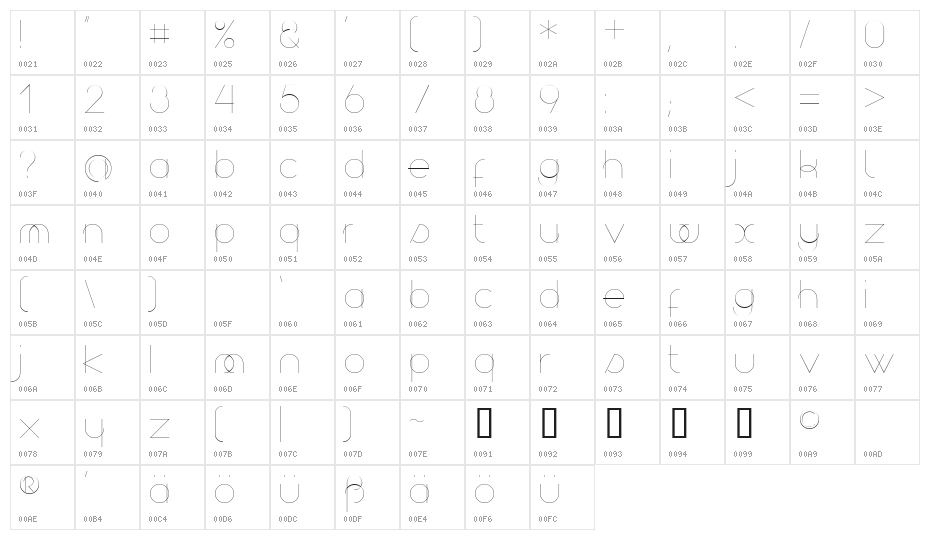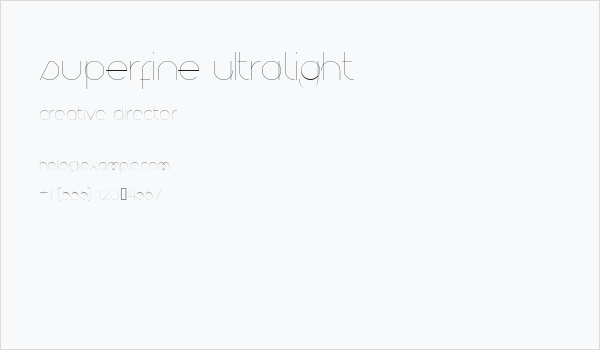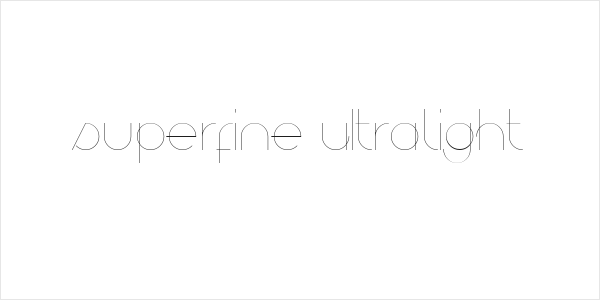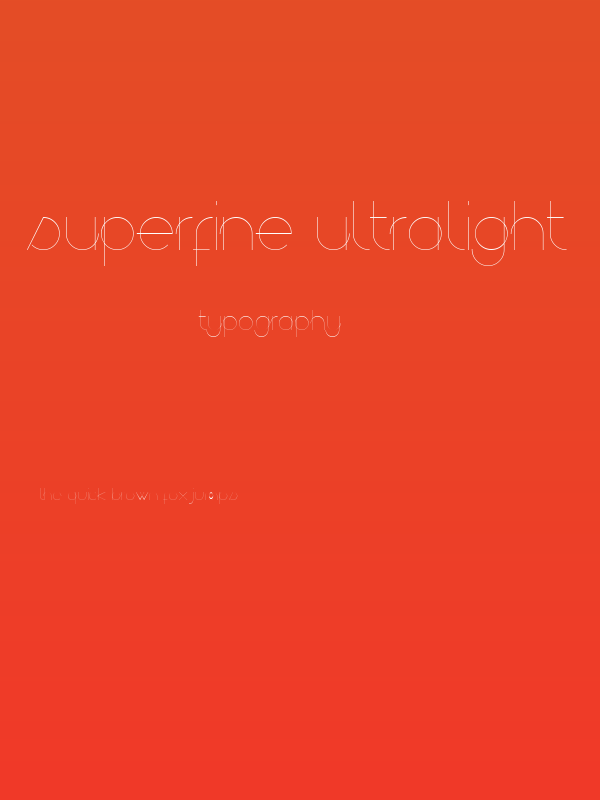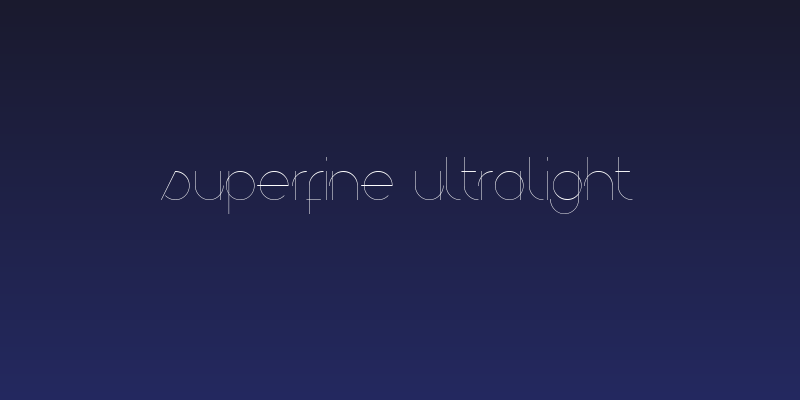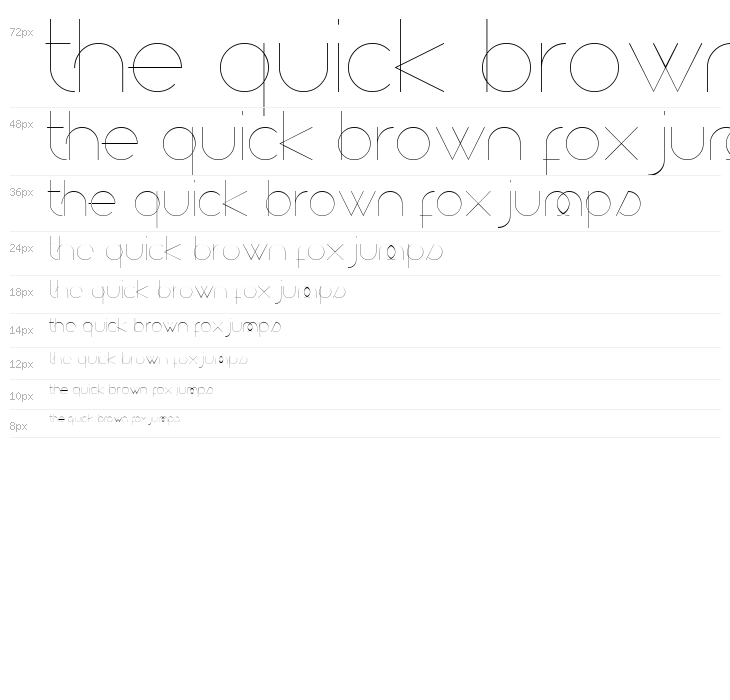
superfine UltraLight Font
Font by Sven Stuber - www.superlooper.de
| الفئات | Modern |
| حالة الاستخدام | Logos, Headlines, Editorial design |
| مشاريع مقترحة | Ideal for luxury branding, fashion editorials, minimalist design projects, and high-end product packaging. |